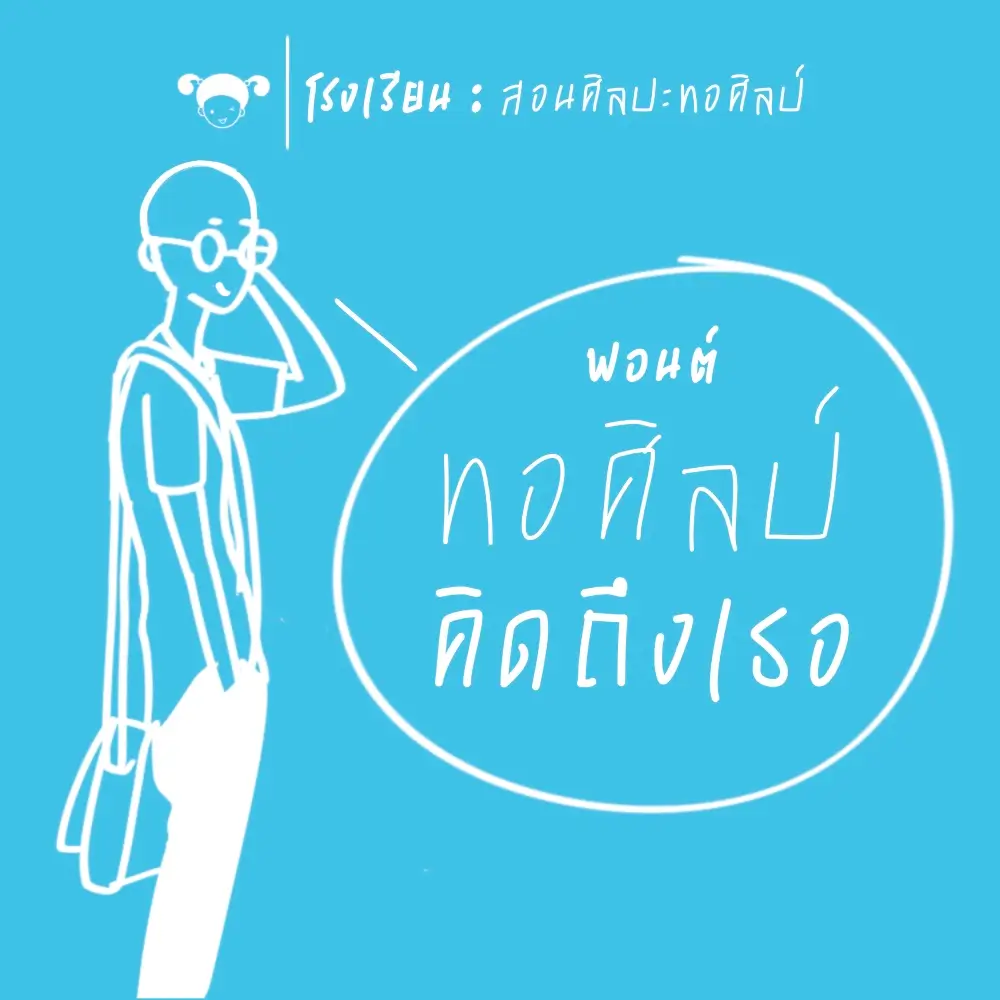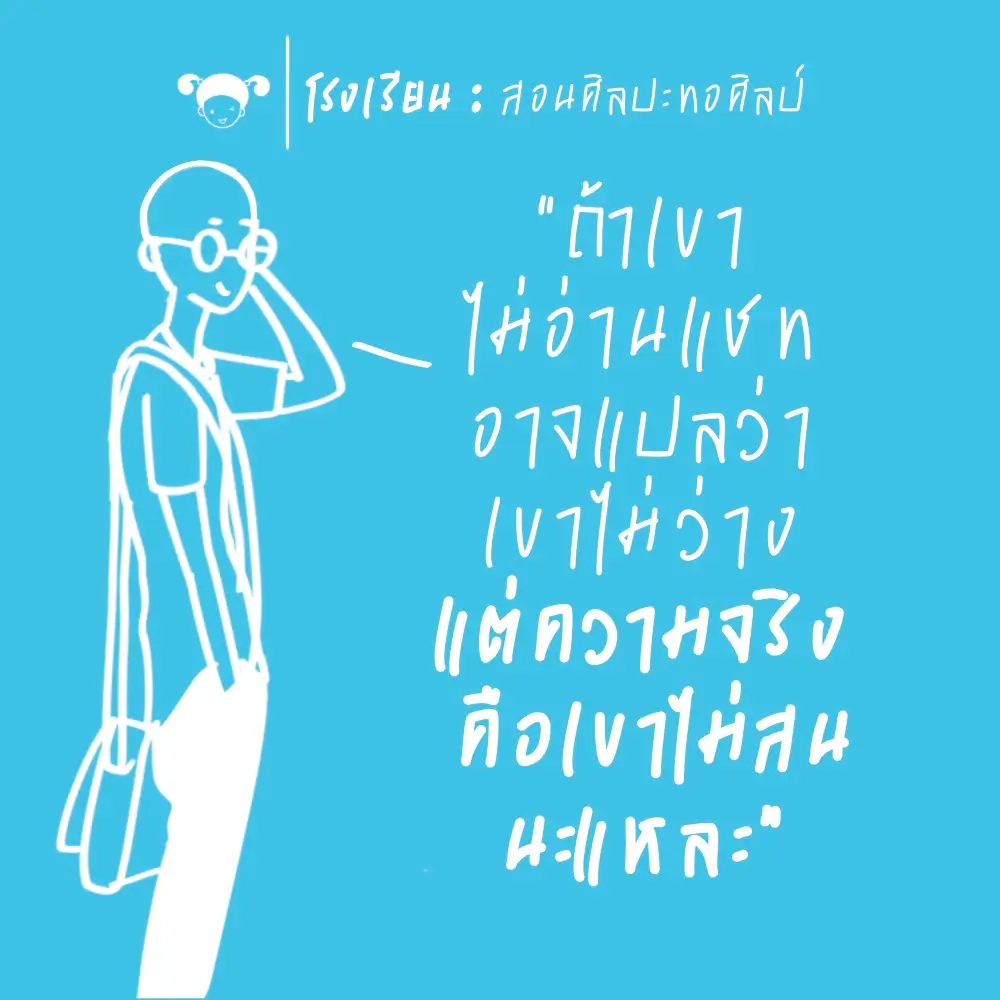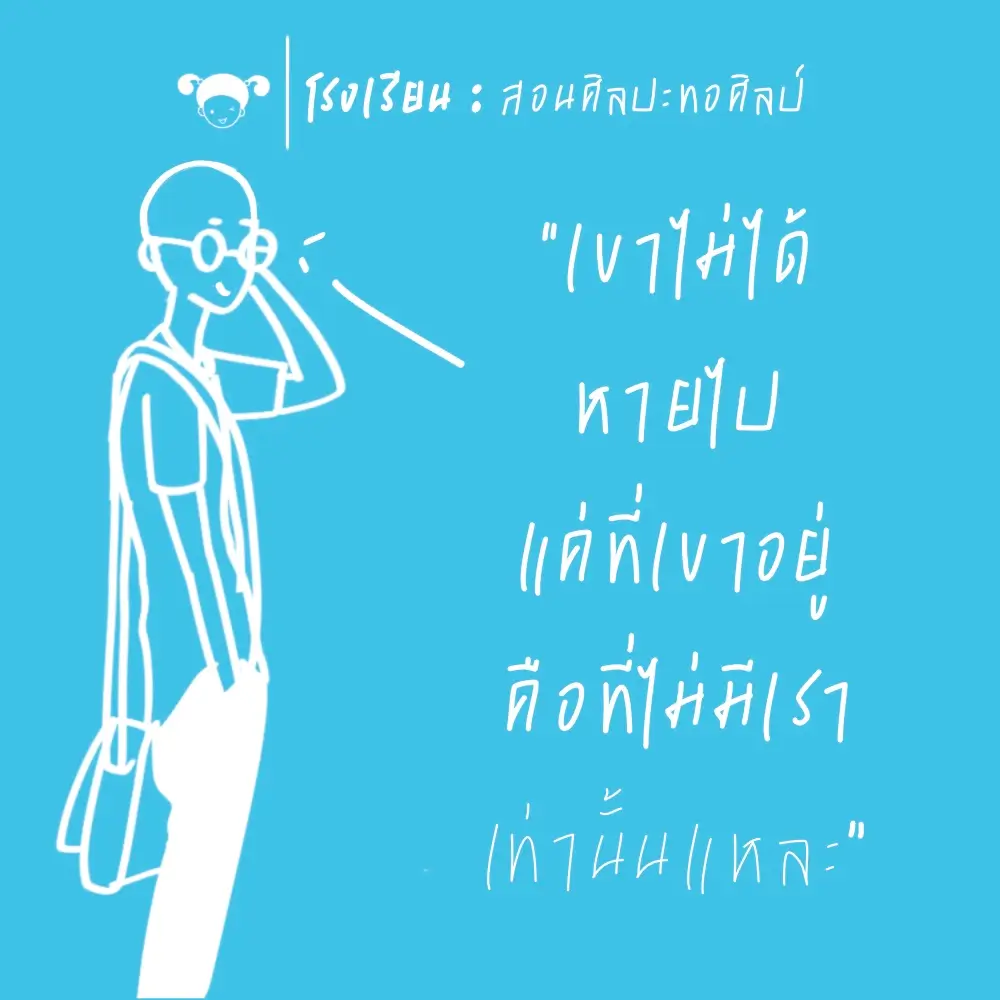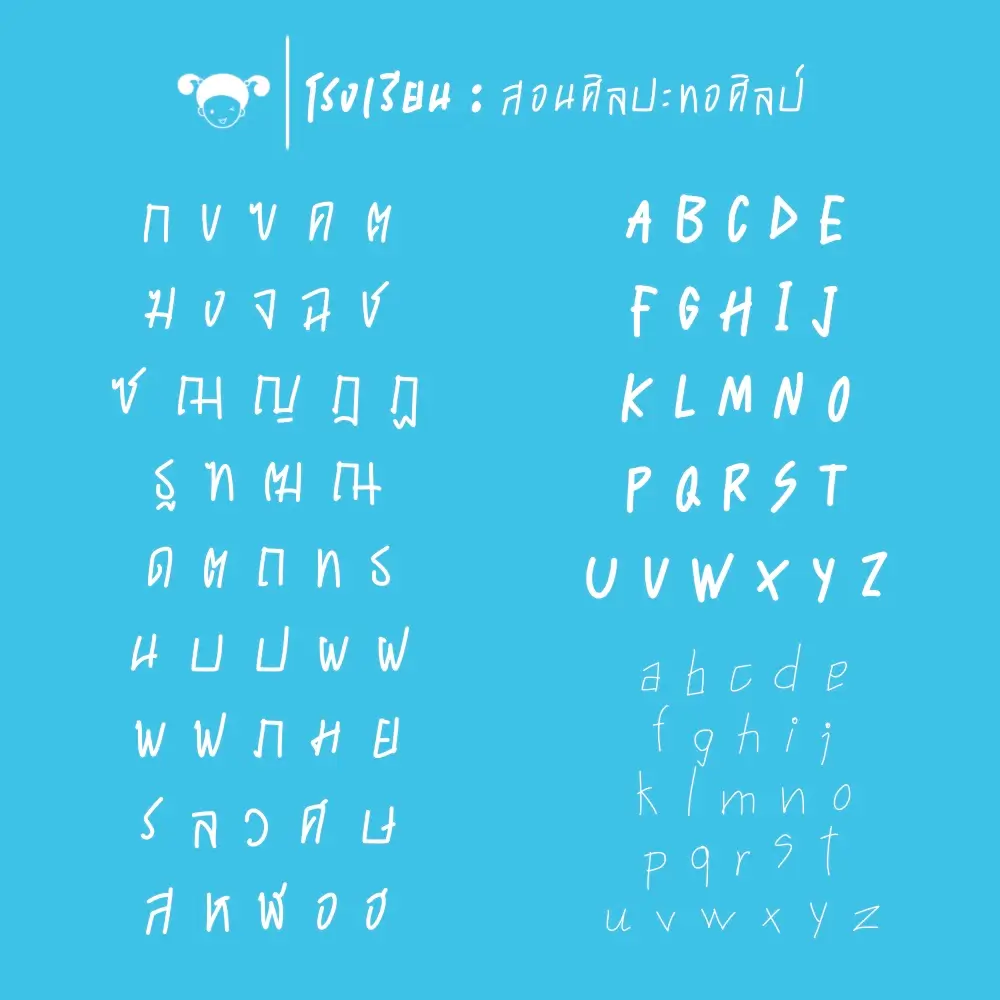
ฟอนต์ “ทอศิลป์ คิดถึงเธอ” เป็นฟอนต์ลายมืออีกตัวนึง จัดวางแบบจังหวะขึ้นๆ ลงๆ เก๋ๆ เป็นธรรมชาติ
ทำมาสามน้ำหนัก (หนา / ธรรมดา / บาง)
ทอศิลป์ คิดถึงเธอ (Torsilp Khitthueng Thoe)